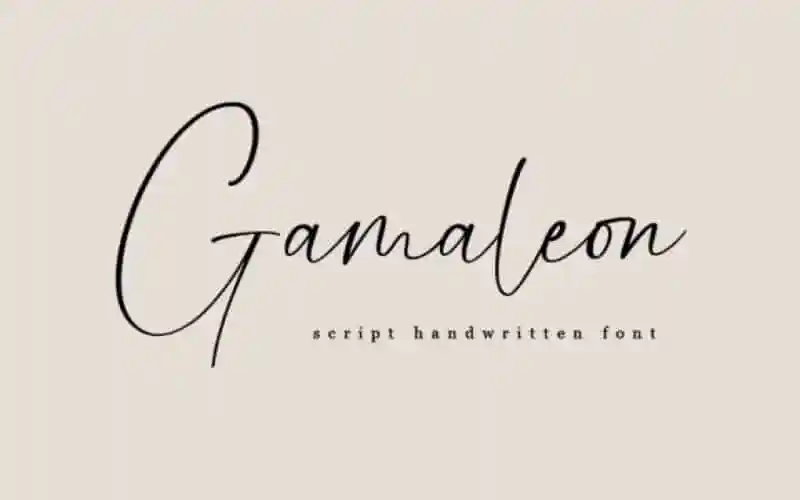
Gamaleon Script Font é uma fonte script fluida que inspira com sua elegância. Perfeita para seus projetos favoritos, a Gamaleon possui características únicas e belas em cada letra, tornando seu design vibrante e incrivelmente autêntico. Essa font foi criada pelo font designer Dav studio. Seu uso em logos, marcas e frases destacadas traz um toque de originalidade inigualável à sua identidade visual. A Gamaleon é a escolha perfeita para quem deseja criar designs memoráveis que chamem a atenção dos olhos do consumidor. Com certeza vai deixar seu design sobressair no mundo digital.